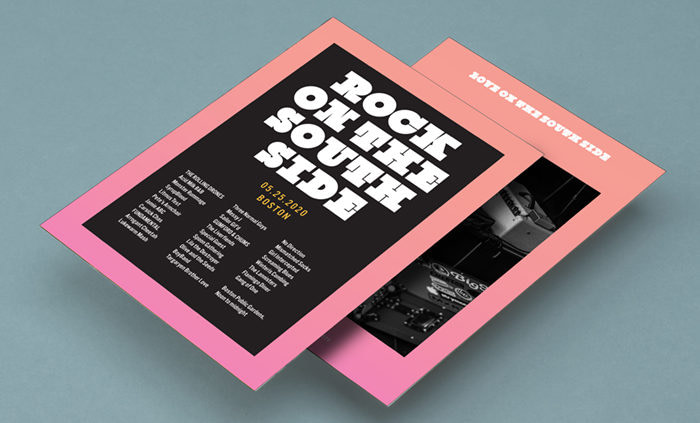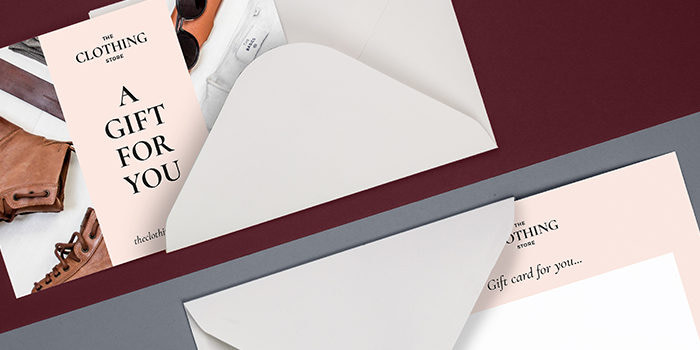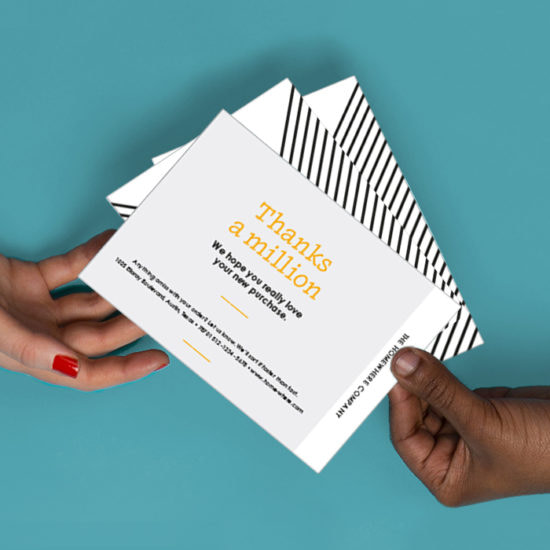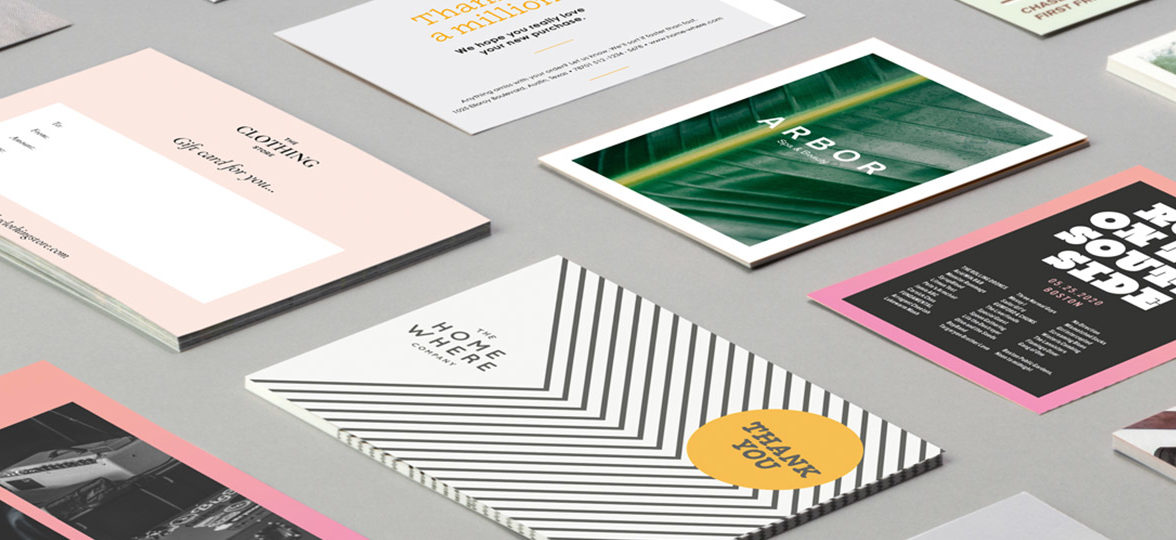
5 font (diversi da Helvetica) con cui raccontare il tuo marchio
Abbiamo scelto 5 font per ispirare e deliziare, da quelli gratuiti ai classici meno conosciuti, fino ai caratteri di ultima generazione. Qual è il tuo preferito?
Usa questa selezione di font eleganti per solleticare l’immaginazione, creare design e illustrazioni, o semplicemente per dare un po’ di dolcezza tipografica alla giornata…
Akzidenz Grotesk
Nonostante il nome poco lusinghiero (nel linguaggio dei font, “grotesque” significa semplicemente “senza grazie”), questo font pulito e ordinato gode di una fama notevole come primo sans serif in assoluto. Trasmette un’impressione di calma e chiarezza con un accenno di morbidezza.
Akzidenz Grotesk è disponibile in una miriade di varianti diverse grazie alla popolarità che lo ha reso un precursore: creato a Berlino nel 1896, il font ha ispirato una nuova ondata di stili senza grazie che dalla Germania si è estesa al resto del mondo. Oggi è il font ufficiale della Croce Rossa Americana, e compare anche nel branding di varie squadre sportive statunitensi come i Brooklyn Nets.
Basic Commercial
Nato nel 1900, questo font sembra immune agli acciacchi dell’età. Deve i natali alla Linotype, azienda pioniera nel settore della stampa a piombo fuso. Un font intramontabile, sintesi delle caratteristiche tipografiche dell’epoca. Da quei giorni lontani ne ha fatta di strada, mietendo un successo dopo l’altro, ispirando nuovi stili senza grazie e facendo bella mostra di sé nei luoghi dell’immaginario collettivo (uno per tutti? Le fermate della metro di New York). È versatile, duttile, senza tempo. Insomma: il font dei sogni.
Black Slabbath
Come resistere a un tale gioco di parole? Soprannominato “il font più pesante del mondo”, Black Slabbath appartiene al gruppo dei caratteri egiziani ed è ideale negli slogan o nei titoli di grandi dimensioni e d’impatto. Lo spazio bianco ridotto al minimo contrasta con le lettere massicce, bilanciandone l’impatto. Da non confondersi con il font svolazzante usato dalla quasi omonima band metal degli anni Settanta, questo font più recente risale al 2008.
Cormorant
Altro carattere gratuito molto amato, Cormorant è un font Google che nasce come omaggio al classico Garamond, risalente al XVI secolo. È un carattere con grazie dall’effetto alternato spesso-sottile che evoca una calligrafia delicata, nonostante sia abbastanza chiaro ed essenziale da poter essere utilizzato sia nei paragrafi di testo che nei titoli.
In Cormorant, l’effetto sofisticato ma familiare di Garamond è stato rivisitato in chiave moderna, accentuandone i contrasti di spessore. I punti più netti e definiti e le linee più sottili vantano una precisione a prova di pixel impensabile all’epoca della tipografia analogica.
Inkwell
Un font calligrafico che in realtà *così* calligrafico non è, Inkwell ha molte varianti che vanno dall’elegante e professionale al divertente e quasi buffo. Ciascuna di queste incarnazioni offre il calore e la personalità della scrittura a mano, da quelle più formali, adatte a raccontare una storia nel corpo di un testo, a quelle più originali, declinate in forme runiche e decorate a mo’ di scarabocchio nei titoli e nelle illustrazioni. L’intero set da 48 pezzi di questo font è piuttosto costoso, ma il venditore lo offre anche in vari pacchetti più piccoli ed economici, a seconda dello stile desiderato.